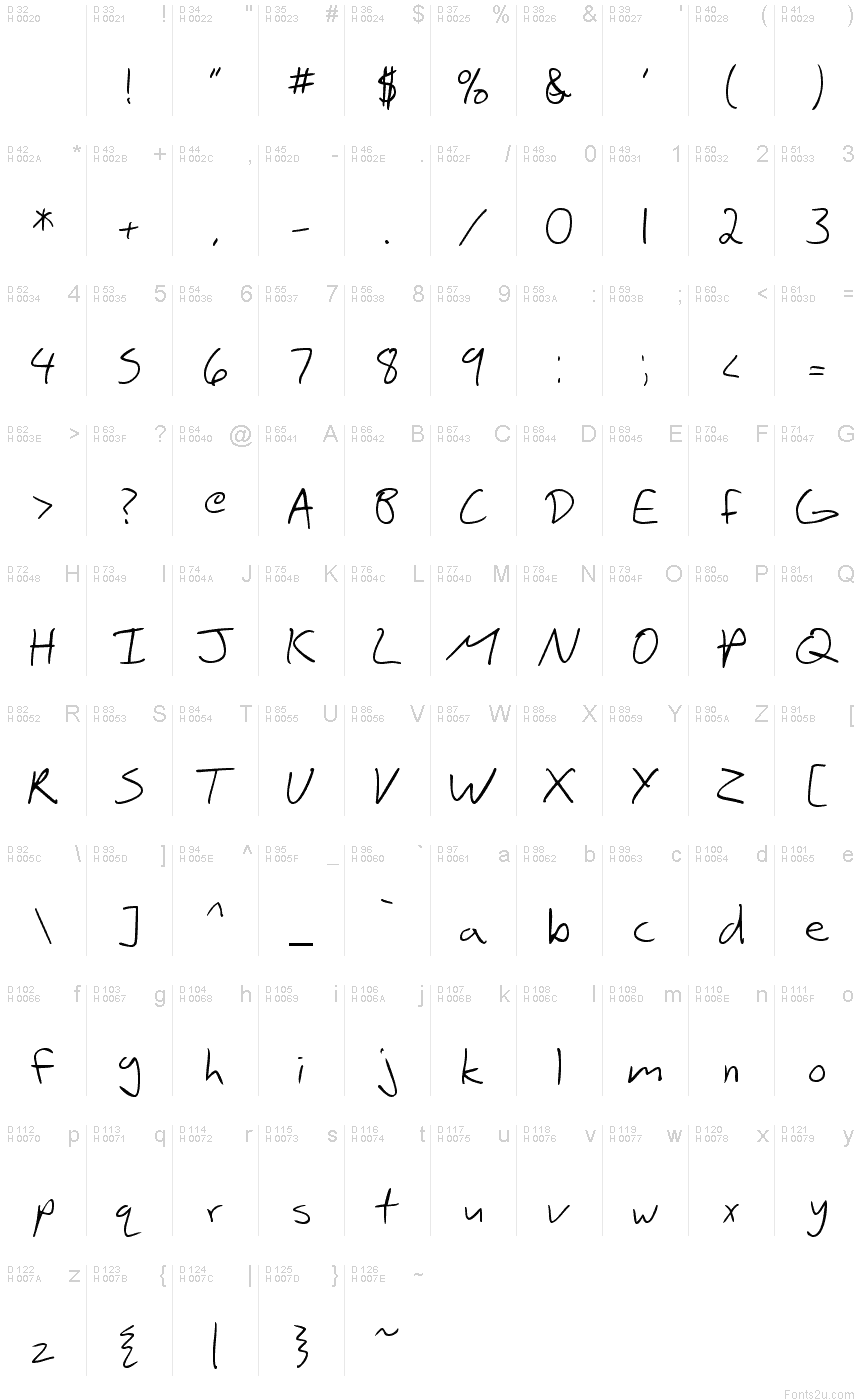
SF Scribbled Sans
SF Scribbled Sans od ShyFonts Type Foundry to darmowy krój pisma w stylu odręcznym z 1999 roku. Luźne, przypominające pociągnięcia flamastra kształty lekko falują i zapętlają się, nadając całości dynamiczny, nieformalny charakter. Choć litery opierają się na prostej bezszeryfowej strukturze, nierówne krzywe i swobodnie krzyżujące się formy sprawiają wrażenie notatki sporządzonej w pośpiechu.
Świetnie sprawdzi się na plakatach, fanzinach, okładkach płyt indie, ulotkach szkolnych czy w zabawnym projektowaniu opakowań, gdzie zbyt schludna czcionka wydawałaby się zbyt sztywna. Jako darmowy font, dobrze radzi sobie również w krótkich nagłówkach, na planszach tytułowych czy w szkicach logo, ponieważ pismo wygląda na spontaniczne, ale nie sprawia wrażenia niechlujnego.